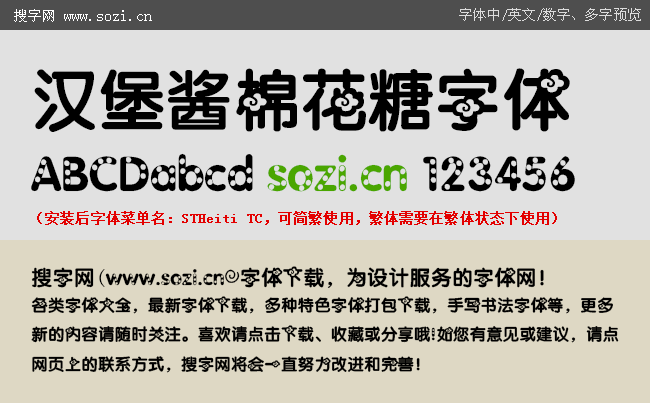
漢堡醬棉花糖字體
搜字網(wǎng)給大家提供一款漢堡醬棉花糖字體手機(jī)中文字體下載。這款手機(jī)字體是以粗圓字體為原形,筆畫間嵌入了可愛的卡通棉花糖圖案。在具備粗圓字體清晰醒目風(fēng)格的同時(shí),卡通味也特別濃,是一款非?蓯鄣目ㄍㄗ煮w,特別適合喜歡手機(jī)字體個(gè)性一些的朋友在手機(jī)上安裝使用。